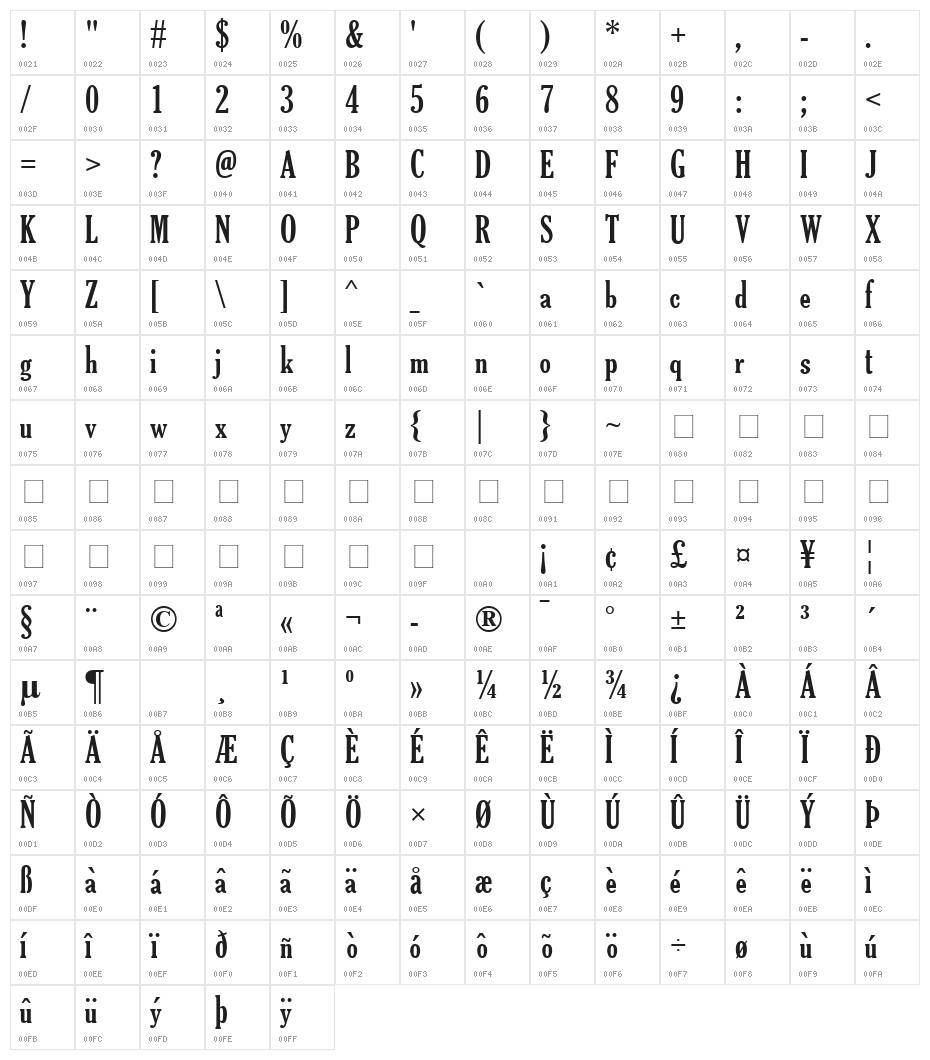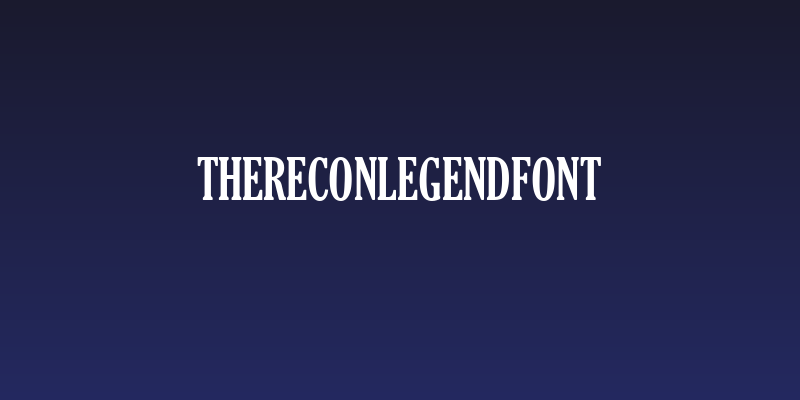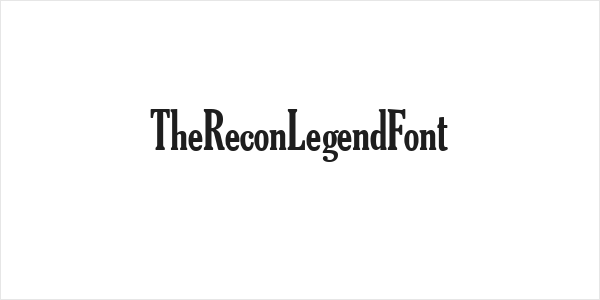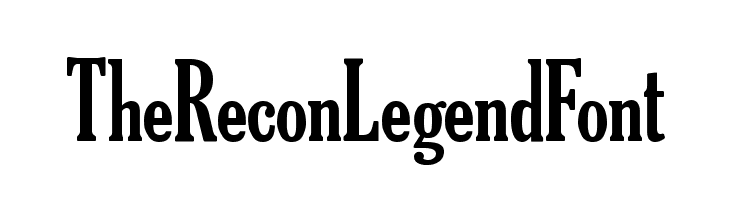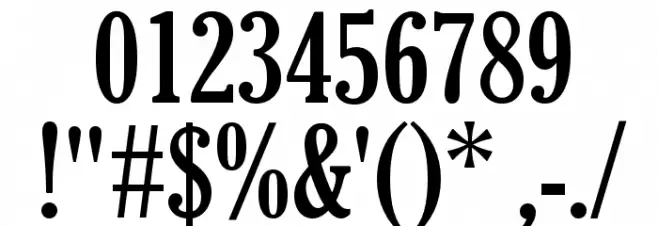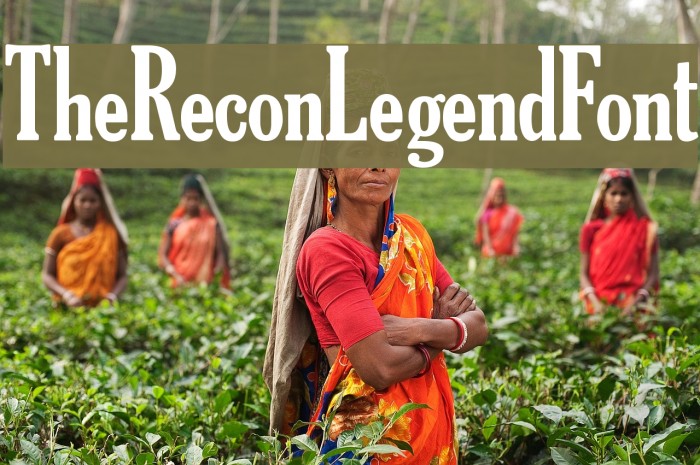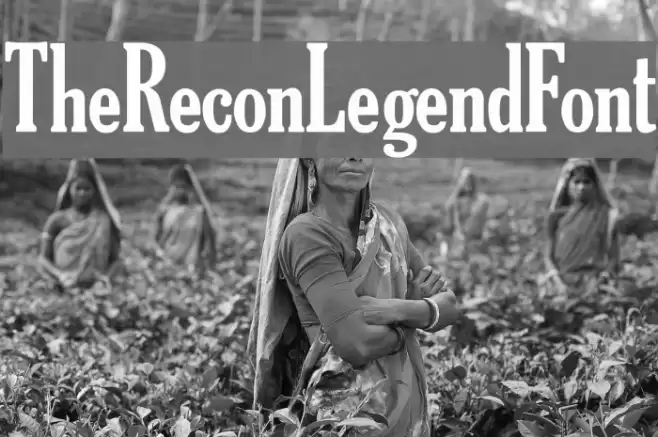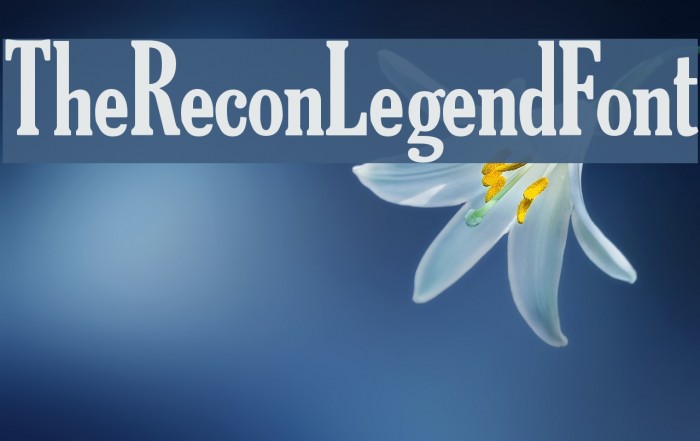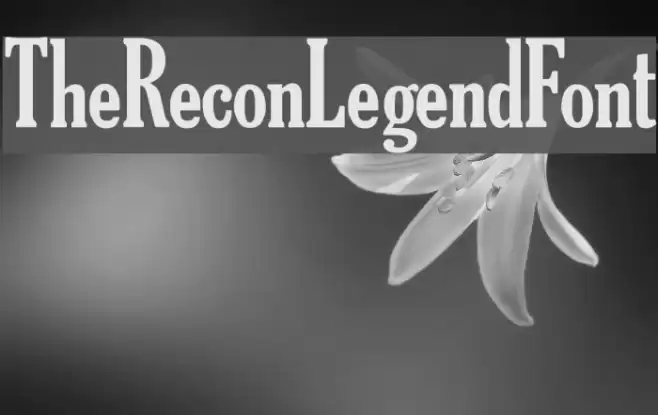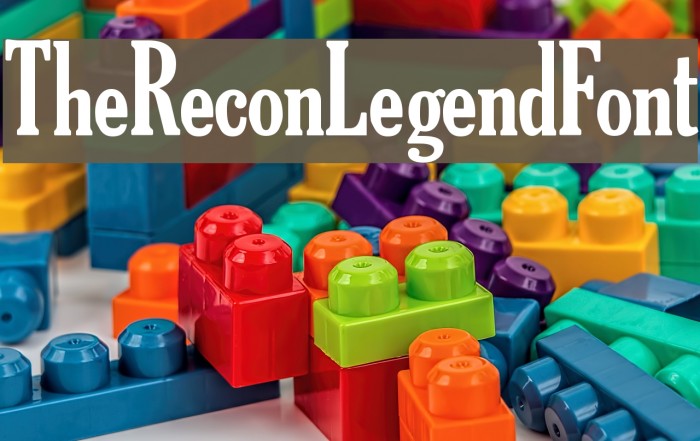
TheReconLegendFont Font
✎ Serif
| الفئات | Serif |
| النمط العام | Classic |
| مشاريع مقترحة | Ideal for headlines, book covers, posters, and branding materials that require a strong and authoritative look. |